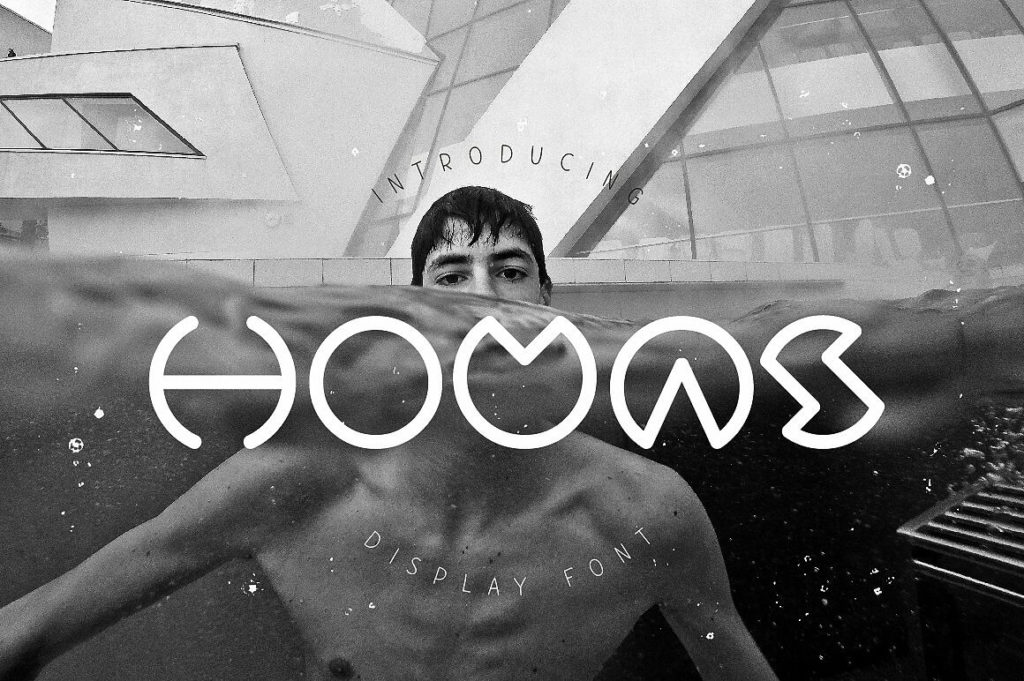
Это выразительное кириллическое начертание от студии **RodrigoTypo**, основанной дизайнером Родриго Арайей Саласом (Rodrigo Araya Salas). Шрифт был выпущен в рамках коллекции *Bundle 15 FONTS* примерно в **2017 году**. Автор известен своим вниманием к деталям и качественной адаптацией кириллицы, что позволяет использовать этот шрифт не только как декоративный элемент, но и для набора лаконичных текстов. Строгий, но характерный рисунок букв делает его отличным выбором для современных проектов, где важна индивидуальность. Скачать бесплатно можно на нашем сайте, однако перед коммерческим использованием обязательно проверьте лицензию у автора